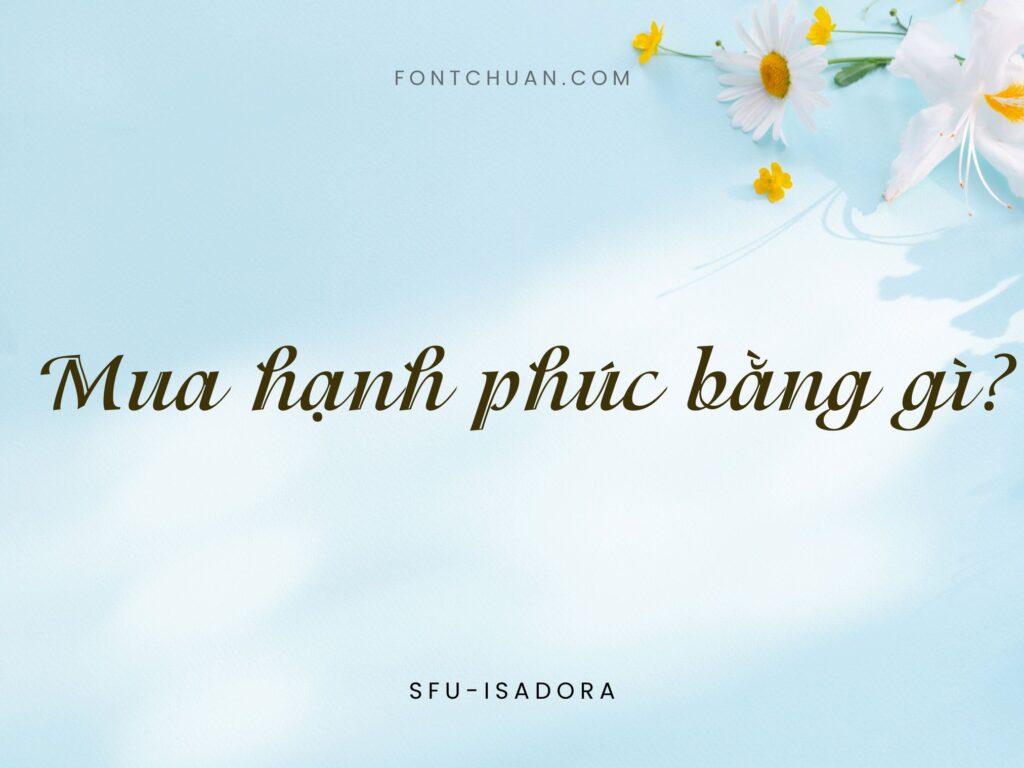
Font SFU Isadora Việt Hóa
Isadora là một kiểu chữ viết tay mang phong cách cổ điển, được thiết kế bởi một tác giả chưa xác định và phát hành trên DaFont. Font này được sưu tầm và đăng bởi thành viên của Font Chuẩn. Với thiết kế tinh tế và độc đáo, Isadora tạo cảm giác thanh lịch và phù hợp cho nhiều mục đích sử dụng khác nhau, đặc biệt khi ứng dụng như một Font chữ ký để tăng thêm nét cá nhân hóa và sự sang trọng trong thiết kế.
Về mặt thiết kế, Isadora nổi bật với các đường nét mềm mại, uyển chuyển, tạo cảm giác gần gũi và thân thiện. Font này hỗ trợ nhiều ngôn ngữ và bao gồm các ký tự đặc biệt, giúp người dùng dễ dàng tùy chỉnh theo nhu cầu. Isadora thường được sử dụng trong các thiết kế thiệp cưới, thiệp mời, logo, và các dự án cần sự lãng mạn và tinh tế. Các ngành nghề như dịch vụ cưới hỏi, nghệ thuật, và thiết kế đồ họa có thể tận dụng kiểu chữ này để tạo dấu ấn đặc biệt trong truyền thông.